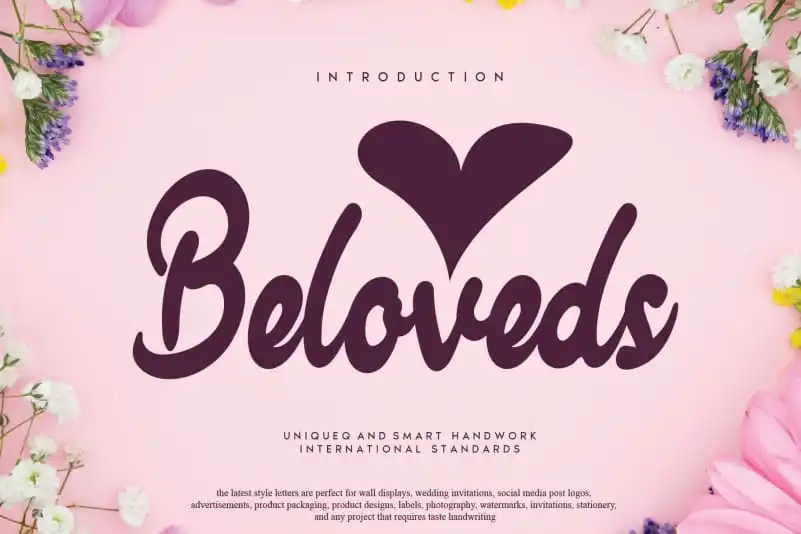
Beloveds Script Font – Download Grátis
A Beloveds Script Font é uma excelente adição para designers apaixonados por fontes escritas à mão. Especialmente criada para experiências de design únicas e inovadoras, essa fonte representa um toque especial que vai enriquecer seus trabalhos digitais. Com formas elegantes e detalhes cuidadosamente elaborados, Beloveds Script é uma opção perfeita para personalizar suas criações de maneira única e sofisticada. Suas linhas fluidas e suaves fornecem um toque romântico que será perfeito para gráficos de aniversário, cartões personalizados ou até mesmo logotipos. Perfeita tanto para aqueles que desejam um pouco mais de romantismo em seus projetos digitais quanto para os criativos que valorizam uma mão na obra autêntica e detalhada. Seja você um profissional de design ou um amante da arte, a Beloveds Script Font pode transformar sua experiência com o texto digital.